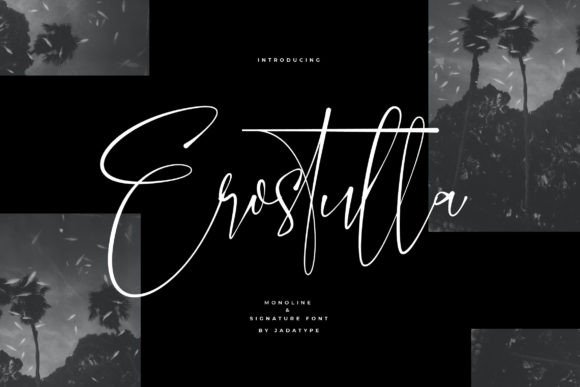
Erostulla
Jika anda sedang mencari aset berkualiti tinggi seperti Erostulla, pakej premium ini merupakan pilihan yang hebat untuk projek kreatif anda.
Sama ada anda mencipta produk POD (Print on Demand), jemputan perkahwinan atau grafik media sosial, Erostulla amat bersesuaian.